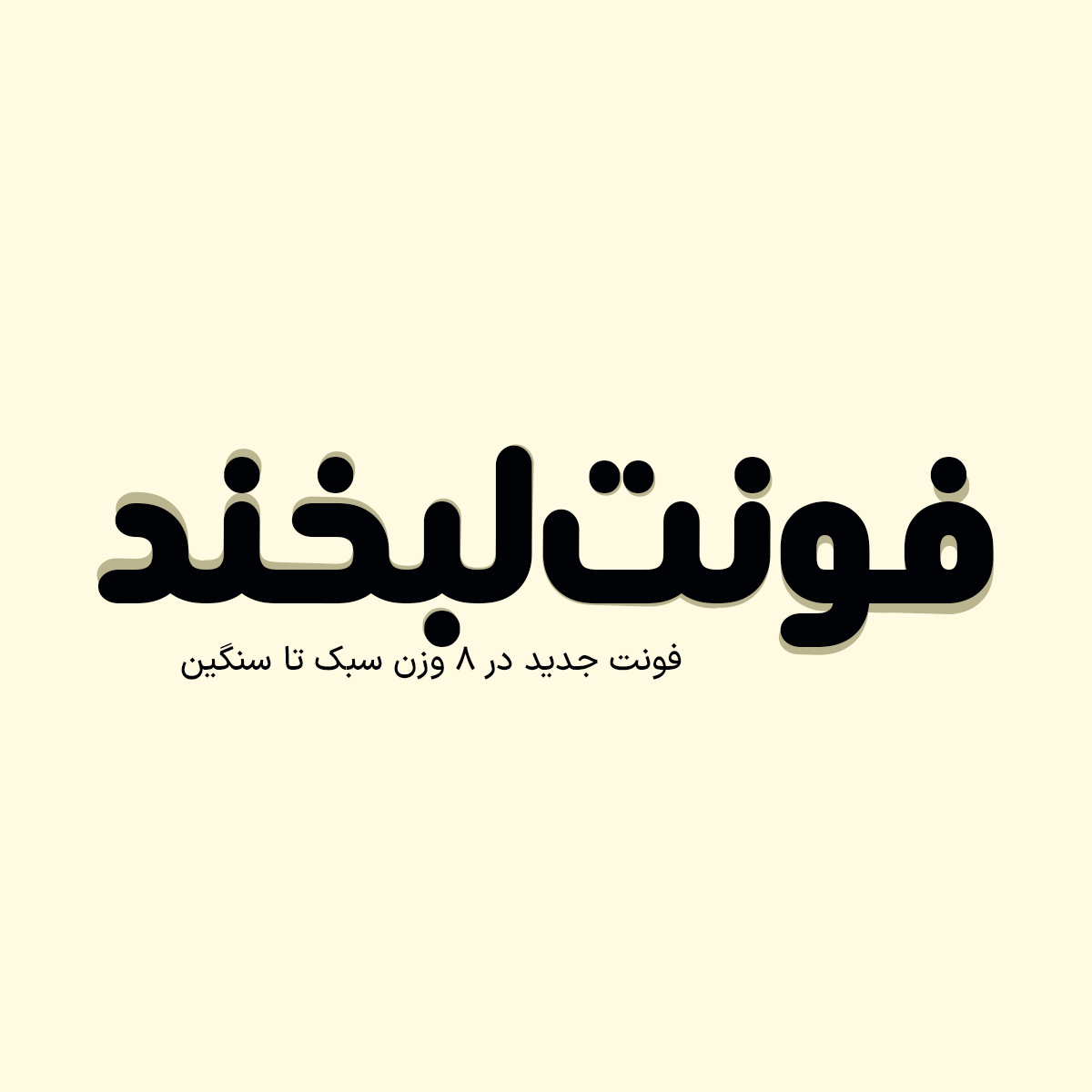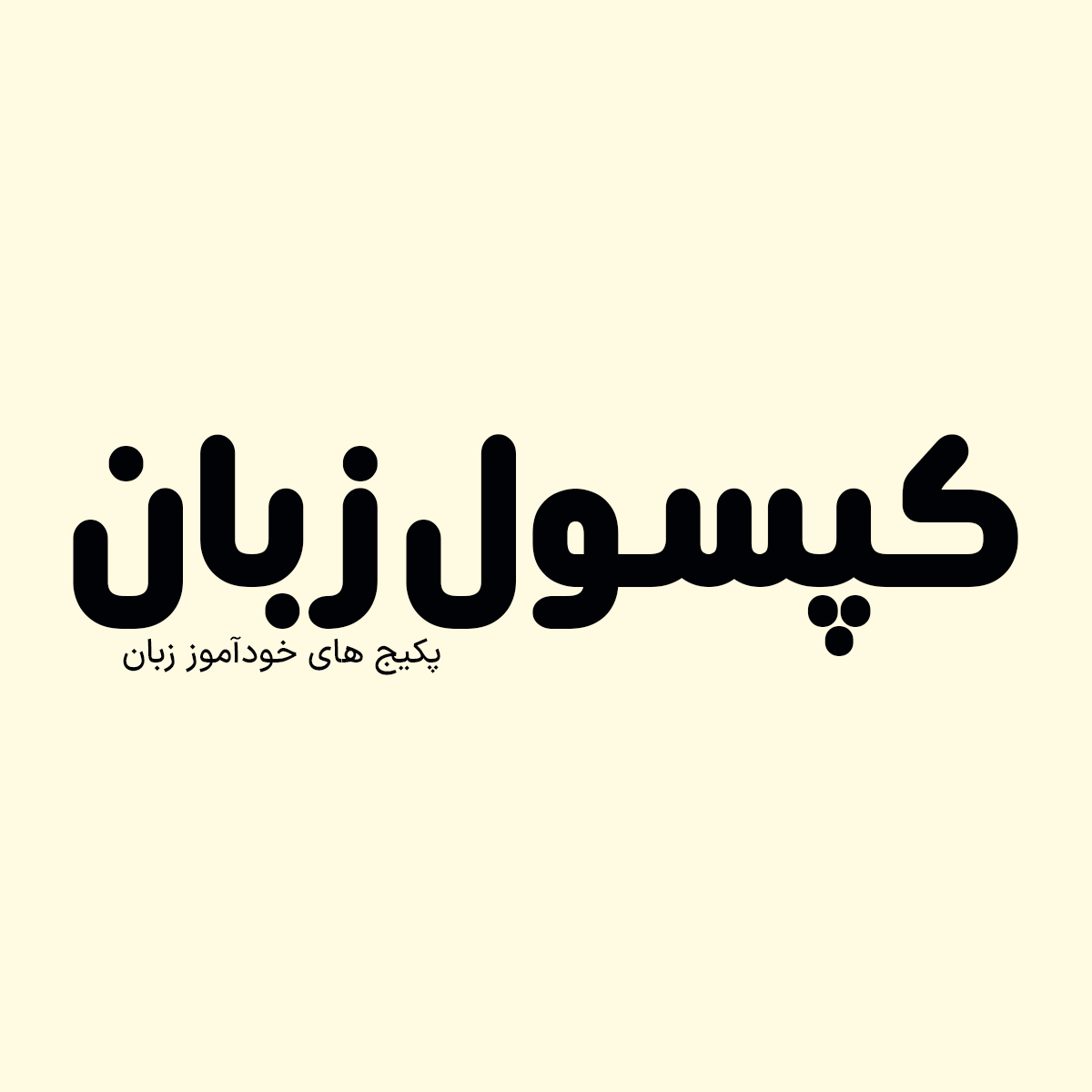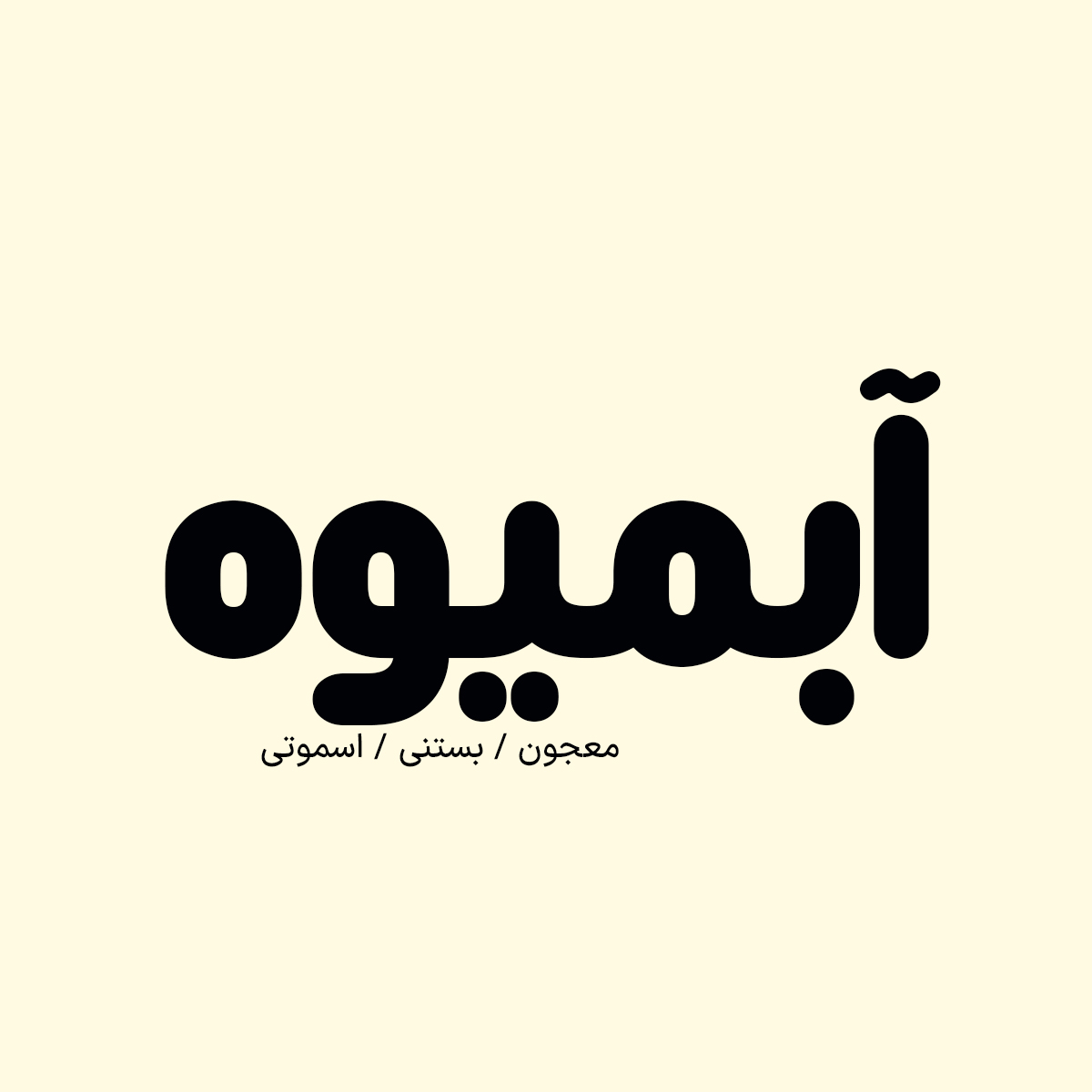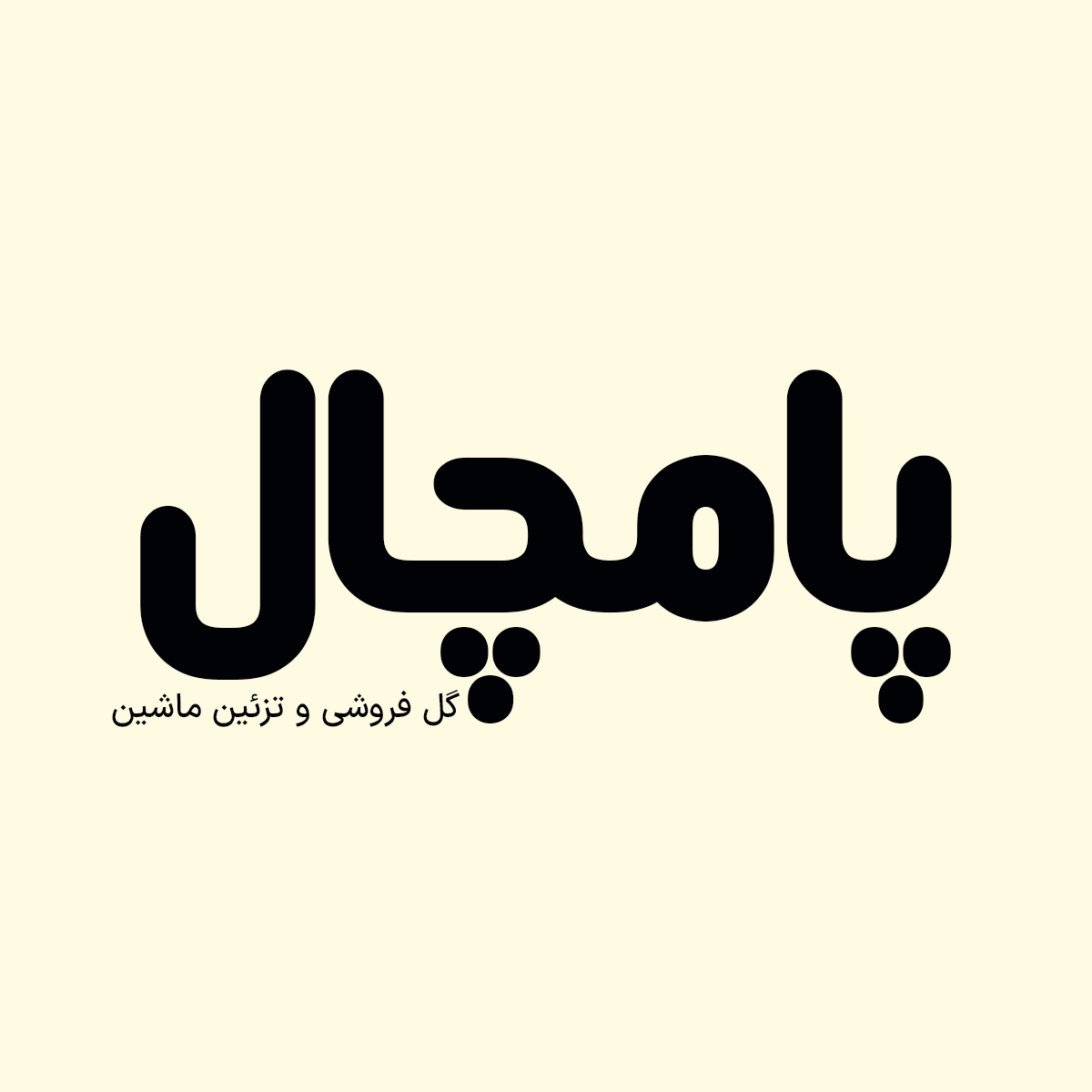
فونت فارسی لبخند Labkhand Font
فونت فارسی لبخند یک فونت گرد، لطیف و دلنشین برای پروژههای فارسی به خصوص طراحی انواع لوگوتایپ و تایپوگرافی می باشد که شما با استفاده از…
فونت فارسی لبخند یک فونت گرد، لطیف و دلنشین برای پروژههای فارسی به خصوص طراحی انواع لوگوتایپ و تایپوگرافی می باشد که شما با استفاده از فونت لبخند میتوانید لوگوتایپ و طراحی های زیبایی خلق کنید.
فونت لبخند با طراحی منحصربهفردش، مناسب طراحی پوستر، بنر، شبکههای اجتماعی، پروژههای دانشجویی و حتی طراحی رابط کاربری میباشد.
فونت فارسی لبخند که در ۸ وزن سبک تا سنگین طراحی شده است با الهام از سبک لوگوتایپ آزاد و روان طراحی شده؛ که نه زیادی رسمی هست و نه زیادی فانتزی. سادگی همراه با حس رسمی، حروف نرم، کشیده و متعادل. در ادامه برای شما نمونه تایپ های این محصول حرفه ای رو آماده کردیم که میتونید مشاهده کنید.
پیشنمایش و نمونه تایپ های فونت لبخند